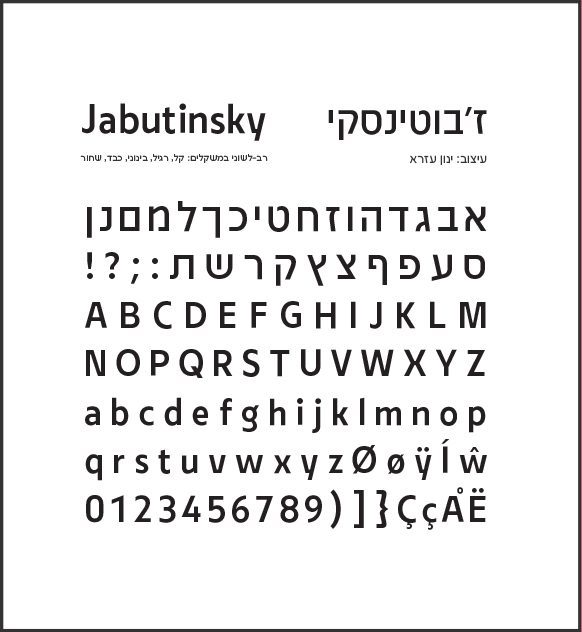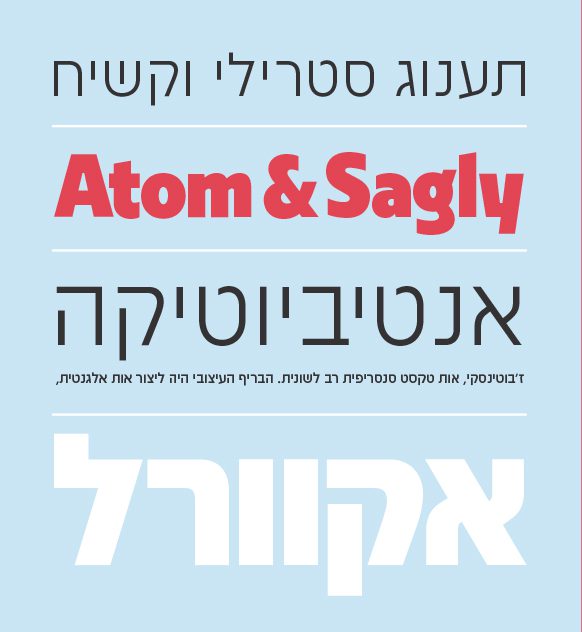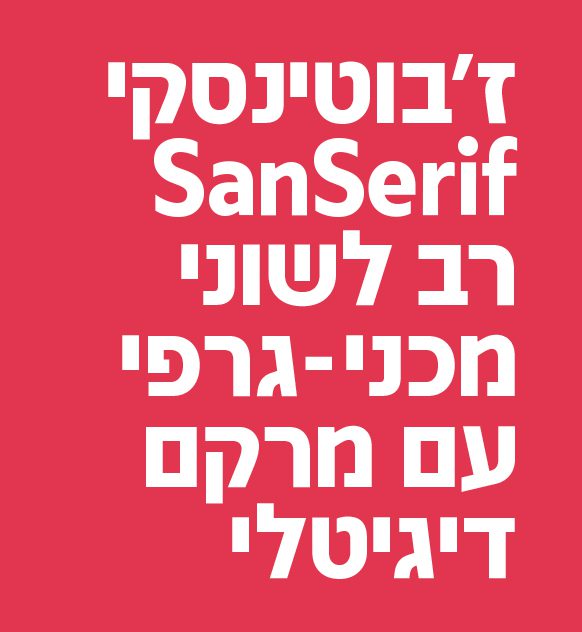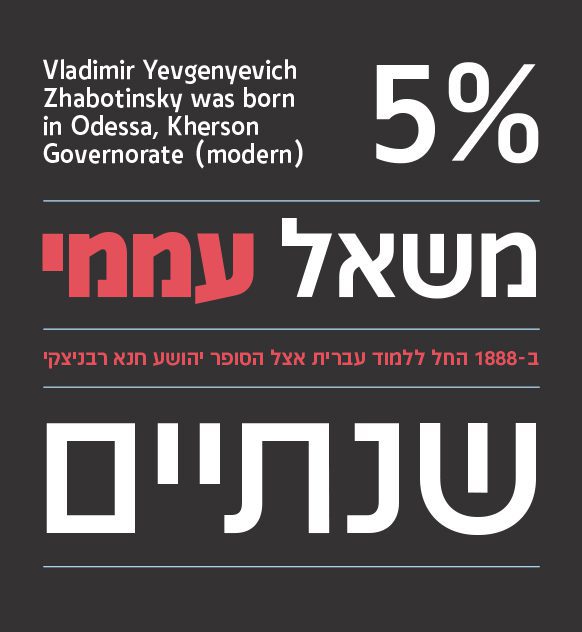
ז'בוטינסקי
ז'בוטינסקי / Fb Jabutinsky
• שם הגופן:ז'בוטינסקי
• מעצב הגופן:ינון עזרא
• סגנון:סאן סריף
• מאפיינים: קל רגיל בינוני כבד שחור
• תכונות: אוונגרדי אלגנטי מגזיני מרובע פשוט קשיח
סיפור הגופן:
גופן ז׳בוטינסקי, אות טקסט סנסריפית רב לשונית. הבריף העיצובי שהנחה אותי במהלך העבודה על הגופן, היה לייצר אות אלגנטית, יציבה ופשוטה, שיכולה לשמש כגופן בסיס לעבודה ורסטילית. לגופן חמישה משקלים; בנוסף ישנו סט של משקלים צרים תואמים המעומדים בנפרד בהמשך.